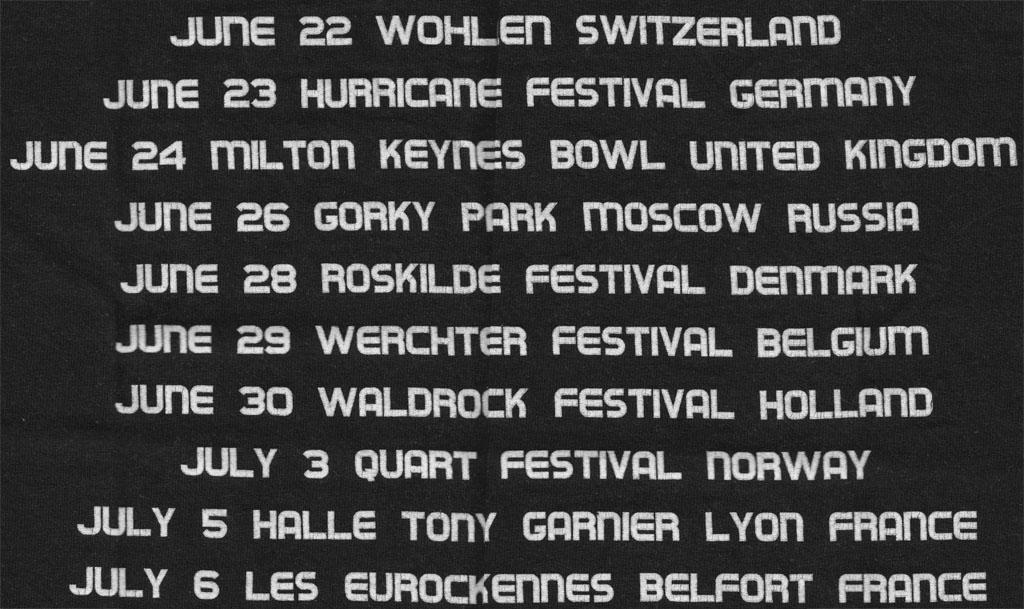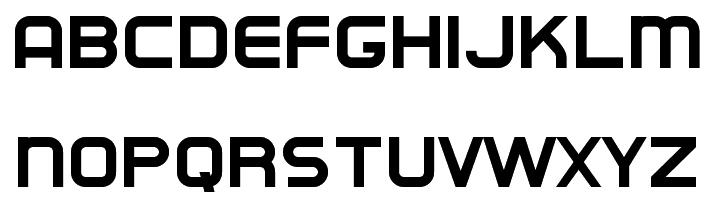
Schrift aus Tourdaten
Suche diese leicht spacig anmutende Schrift. Ein paar Buchstaben sind sehr charakteristisch, aber ich konnte sie bisher nicht finden.
*Edit: Das T-Shirt ist aus dem Jahre 2001